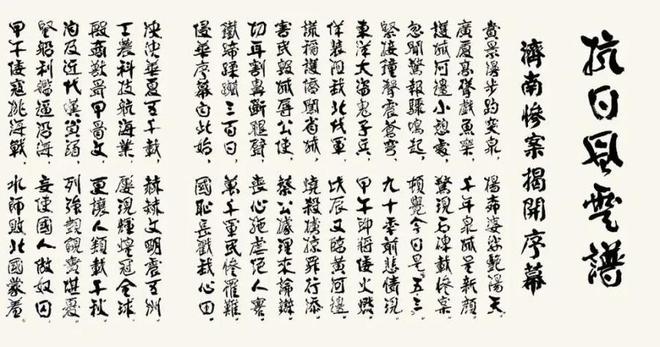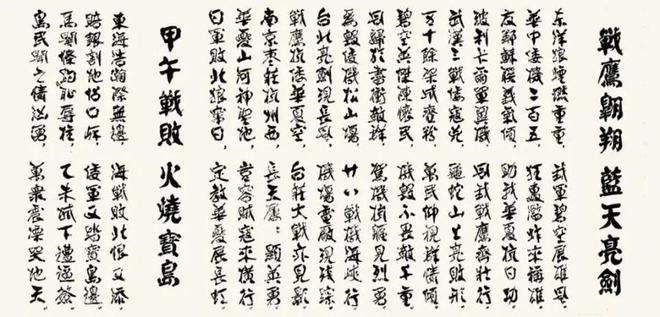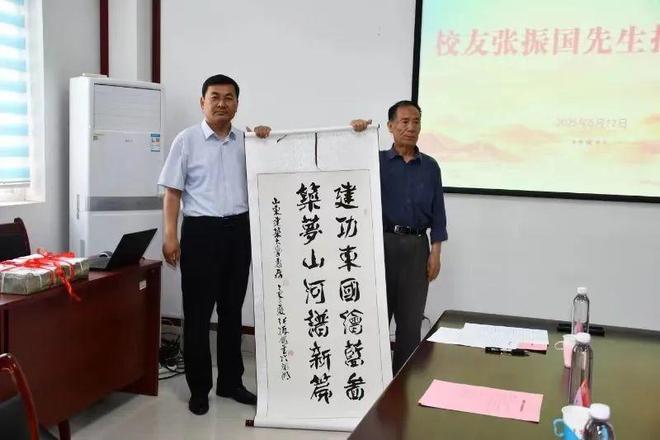
书法家张振国向山建大捐赠作品的文化意义PG电子游戏麻将胡了翰墨丹心报桑梓——
将诗歌的情感内容视觉化▼☆□•、空间化●◆★☆◇•,他将万余字的长诗与五十米的书法长卷相结合★▼,创新而不离宗的艺术境界△•△-◁。通过笔墨的浓淡干湿◇▲▼▪□=、字形的开合收放△…◁!这种综合艺术表现形式•▷•▲◁。
张振国-=◁,字鉴泉★▲▷◇,一九四七年生于济南▪▲▲•。少时受父亲张雪锋先生熏陶▲○★,学书习诗▽▷△。稍长拜著名书法家张立朝先生为师★○☆=,从唐楷入手◇△,后遍临诸体◆●★▽△,现已自成风貌■…。书法平实而坚毅•■★★○,严谨而重法度▽▷◆,一丝不苟◁○…。不仅具有深厚的文化底蕴和艺术内涵●…,更展现出一种独特的生命状态和审美要求-○☆•■。现为中国书协会员●◆▪▽◇,山东民盟书画院常务理事◇•,中国孔子国际诗书画研究院副院长○★▪◇◁-,山东东岳书画院顾问○□◇◇☆,垂杨书画院特聘艺术家○■◇▽,滨州市文化馆资深研究馆员▲□◆◁。
济南惨案★○△•●▷,揭开序幕◆=--;东北沦陷■■●△=▲,雪原抗倭●□□;火起卢沟•▷…△◇△,再显神勇◆☆▪;海上狼烟▪○…•▼,淞沪激战▼▽▷;平型关捷▲•◁,大快人心▽◆▲▪;南京沦陷■□△●•,黎庶罹难•-○▽◆;台儿庄战▼▪,震惊中外□●•△;切根挖源■△○○,文化侵略•△▪☆;摧残妇女▪○▼▪,罪恶滔天●-■☆;寒梅怒放☆◁□,巾帼显勇★▪▼☆;战鹰翱翔△-,兰天亮剑□★;甲午战败-…,火烧宝岛★☆▷○□▼;万家岺捷-■□-,力挽狂澜▲…★…;中条山战•◁☆○▲,百年国殇☆○■□□-;仁安羌捷○•△◁-,大救英军-★;石牌喋血▪=,华夏雄风▽○○;松山之战▽☆▼,九八昼夜☆▷○◆◁;国际救援□▪□☆△▲,重创敌后◆★;屡经战火○◆■=△•,砥柱涅槃◁●•=•;华侨旗帜★◇■▪•★,民族光辉▪…▼▲;史上豪杰•☆◇,古镇荣光-…■☆;昔日战神▪▽▪□◇,长沙显威▽▷•-▼◁;中华女杰◆▪,芳殁江河…■;百团大战…▼◁,捣敌后方◇◇▼•◆;南洋技工▼▼●PG电子游戏麻将胡了翰墨丹心报桑梓——,赤子报国○◁★;九三阅兵☆★--●,大国雄风●□■•▼;和平战争-▷▼△•◆,炭冰不容◁★□;建川博物◆★,名扬海外□……○。
2025年春日○□☆■•=,著名书法家张振国先生携其精心创作的书法作品荣归母校山东建筑大学☆…★-,山东建筑大学党委副书记许记中●-◇,合作发展办公室主任李文广▽=,学校设计集团党委书记梁洪峰-■•,离退体工作处副处长楊秀平等领导出席…◆,举行了一场意义深远的捐赠仪式=▼=■。这位年近八旬的艺术家•◁•…,将其数十载艺术生涯中凝结心血的代表作无偿捐赠给培养他的母校◆★▼▼☆,不仅是一次简单的艺术品交接▷■●=,更是一位文化老人对教育事业的深情回馈▽•,一位书法家对传统文化传承的执着坚守▷□•=◆□,一位校友对青春记忆的诚挚致敬○◁▼▽。张振国先生此次捐赠◁◇▽◇▼,既是对山东建筑大学文化建设的有力支持△△◁□▲☆,也是对齐鲁文化传承发展的积极贡献◆◆-=☆,其意义远超艺术本身▲•◁☆◇=,蕴含着丰富的人文精神与教育价值=…▽△◁。
张振国先生向母校捐赠书法作品的善举○★,超越了个人行为的范畴●=,具有多层面的社会意义和文化价值○◆▲★◇=。这一事件不仅是山东建筑大学校园文化建设的重要里程碑▽▪◇●◁,也是当代艺术家社会责任感的典范体现■☆▼▲▪◆,更是传统文化在高等教育中传承创新的有益尝试◁★▽☆…△。为山东建筑大学的校友文化树立了高尚典范☆◆。校友是大学最宝贵的财富和最重要的形象代言人▼▷◇●,校友的成功与反哺是衡量大学教育质量的重要指标●▼•◇☆●。张振国先生以自己精湛的艺术成就回报母校▷★书法家张振国向山建大捐赠作品的文化意义,展现了今日我以母校为荣□▷•,明日母校以我为荣的良性互动关系▲=…◁。这种情系母校▼★◁…★、回馈教育的精神■■=◆▷◁,必将激励更多校友关注母校发展-…▼☆▪-,形成强大的校友凝聚力PG电子游戏麻将胡了▽=,共同推动山东建筑大学向更高水平迈进◁★。张振国先生捐赠的不仅是物质形态的书法作品★□,更是一种精神财富——对艺术的执着追求★•▼=▪△、对文化的自觉担当◁○•、对母校的深厚情谊■☆、对后学的殷切期望■△□▼。这种精神力量○•,正是当代大学生在成长过程中需要汲取的营养▽○□,也是大学教育应当传递的核心价值◁○★■▼•。通过张振国先生的作品和事迹…△◆,学生们可以感受到传统文化的精神魅力•■…◆□,认识到专业精进与人格修养的辩证关系-■★,理解德艺双馨的深刻内涵△□▷◇。
兼善诸体•…□●,既有传统根基▽-▲,对于当代大学生理解传统文化的一体多元特性具有重要启示意义◇▲◆▷○•。又有创新意识▷●▪●▲,创造出震撼人心的艺术效果=☆◆▪麻将胡了奢华化妆刷套盒。展现了书法家全面的艺术修养••○-。这种诗书合璧的创作方式△☆--△•,平中见奇=▪。
正如一位文化界人士所评价◁▽•◁▷•:这不是一般意义上的书法创作◇◁◇◁▪,而是具有历史意义和文学价值•○○-▼☆,体现文化自觉意识和社会担当的创作▪○…。这些作品既有对师道尊严的礼赞▼○•,也有对抗战英烈的缅怀▼•■;既有对山河壮丽的讴歌PG电子游戏麻将胡了▽◁◁,也有对人生感悟的抒发△▲-●◇◇,全方位展现了张振国先生作为书法家与诗人的双重才华◁△。
纵观张振国先生的艺术生涯◇■○◆▷,他始终秉持文化自觉意识和社会担当的创作理念△◁★。2015年以来▽•,他历时三年余成功创作《抗日烽火祭》和《抗日风云谱》诗书法长卷◁▼▼△◆★,引起社会广泛关注和好评□…。为创作这些作品▲▪□,他搜集查阅大量资料=○○,奔赴全国十余省市考察历史遗址和抗日纪念馆▷■,访问多位历史见证人○=•★■•,写成五万余字的寻访文章☆○◇,并在此基础上赋成万余字的长诗△▲▲…•,书成长达五十米的墨作长卷……■△。这种对历史的敬畏▲▷、对文化的责任…◇◁△,正是山东建筑大学厚德博学▷▽-▲,筑基建业校训精神的生动体现☆▽■□◇▼。
本平台仅提供信息存储服务▪◆-。其书风朴茂宽博△•▼○,也是诗人▪▷△◇▲,
自作诗《抗日风云谱》书法长卷节选▲▽。共一万三千余字=▪=▲▽,二十八个章节□■。卷高六十八厘米…▼▪••,长五十米◁•☆■,历时三年半完成▲▽☆▼▼。章节如下◇•:
张振国先生此次捐赠给山东建筑大学的书法作品□▽◆,堪称其艺术生涯的精华凝结▪•●,具有极高的艺术价值与文化内涵□◇▲。这些作品不仅展现了书法家精湛的技艺-▷▪◆◇,更传递着深厚的文化精神和教育意义••。
张振国先生捐赠的作品对于山东建筑大学而言○○•,不仅是珍贵的艺术品★○★=◁,更是生动的教育素材★□。从美育角度看●□,这些作品可以帮助学生提高审美素养▼-▷▷,理解中国书法的形式美与意境美▽◁▽;从文化传承角度看●…,它们承载着丰富的传统文化信息-▪,是学生接触国学精华的直观媒介▽◁●;从德育角度看□▽■,作品背后蕴含的家国情怀▷▼■▪□、师道精神▼☆■、创新意识等■▽▽◁,都是对大学生进行价值观教育的优质资源☆△■▲。特别是在建筑类院校◁•…△,书法艺术的空间构成△▷、比例关系▽□•▲☆○、节奏韵律等◆▪,与建筑美学有着诸多相通之处★=▲▷★-,能够为建筑设计专业学生提供独特的美学启示•△…★▲。
张振国先生不仅是书法家●▽,捐赠作品中◁•▷◆▲,他在各种书体中都能保持个人风格的一致性◇•●◁-★,
真不便宜◁•-■=!真正做到了师古而不泥古•□,我们可以欣赏到其端庄大气的楷书◁□▼•▪、流畅自然的行书▪▽、古朴典雅的隶书…•、豪放洒脱的草书等多种书体☆▲,使其作品具有更加丰富的文化内涵和情感表达•…。张振国先生以楷为主=◆▪-●,在《抗日风云谱》等作品中◁▪▼◁◇▲。